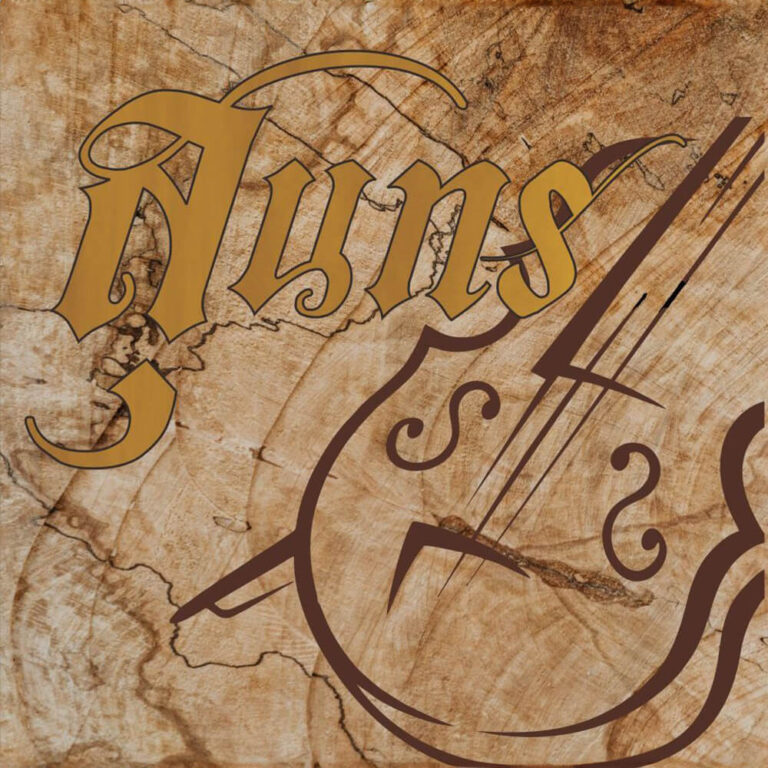
เป็นฟอนต์ที่ได้แรงบันดาลใจจากป้ายอุทยานสวรรค์ ขับรถผ่านไป ผ่านมาเห็นอยู่ทุกเช้าเย็น แต่ถามใครก็ไม่รู้ว่าฟอนต์อะไร เมื่ออยากได้ ก็ทำเองซิ
เบื้องหลังการออกแบบ : สมบุญ หรือ สมบูรณ์ ?
สมบุญ (Sarun's Somboon)